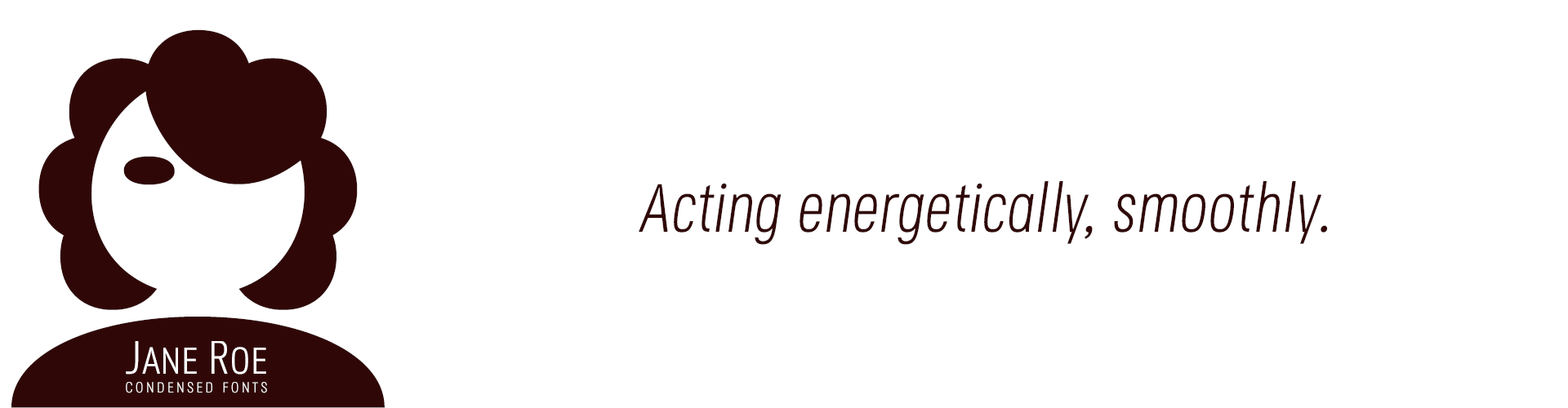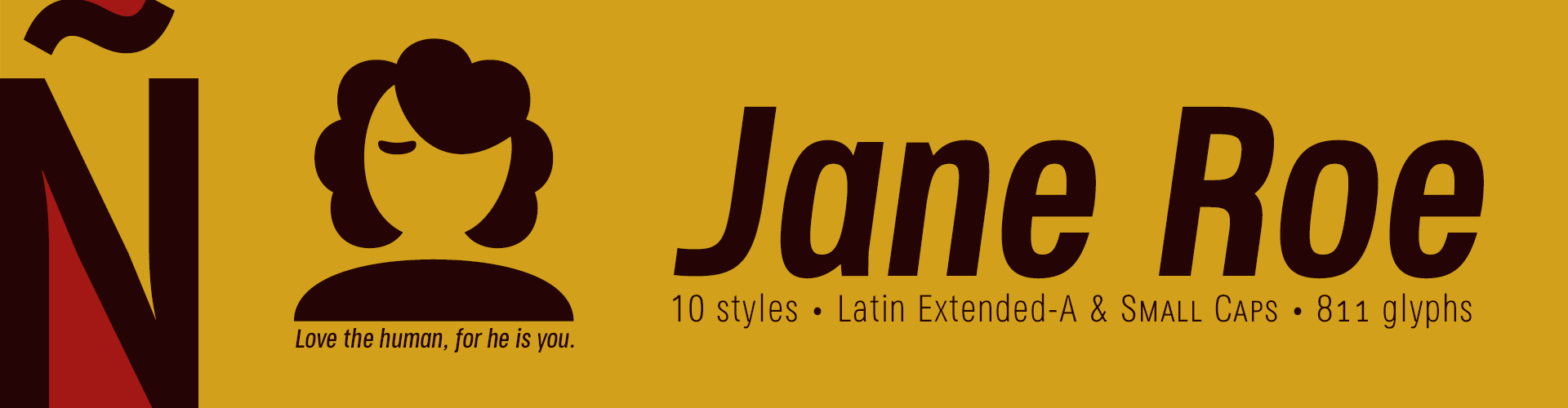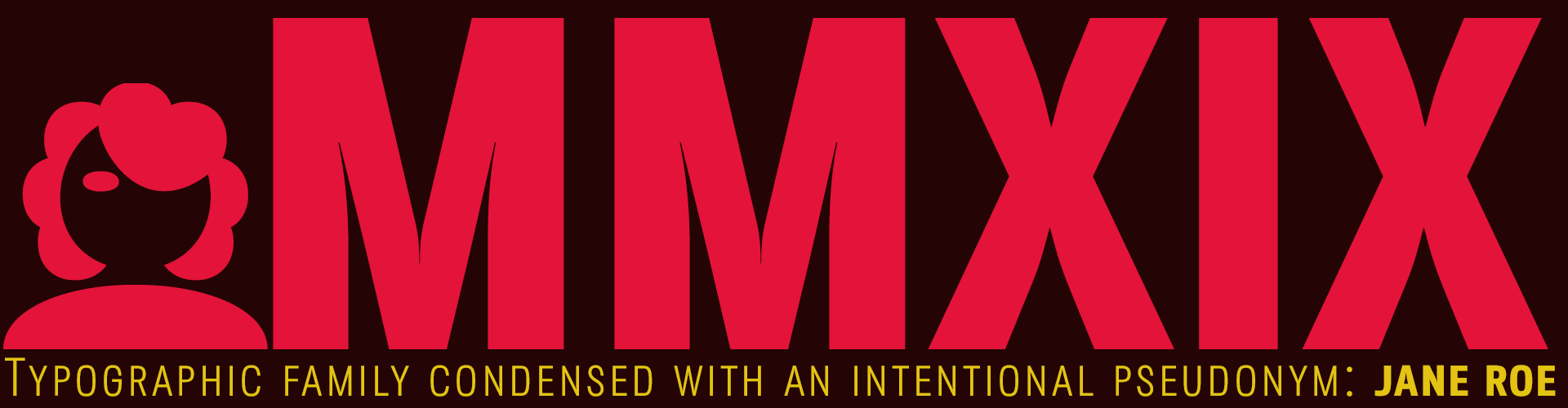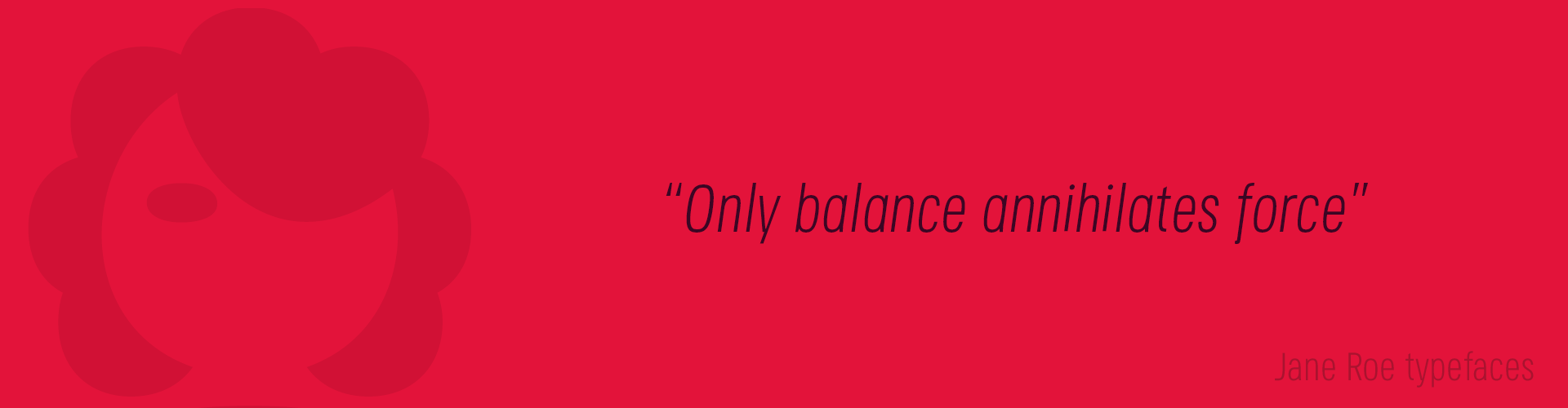
Acting energetically, smoothly!
Estilo: Sans Serif, Neo-Gothic, Condensed, Italic
Proporción: Light, Regular, Medium, Bold & Extra Bold
Funciones OpenType: Additional languages, All Alternates, Alternate Annotation Forms, Capital Spacing, Denominators, Discretionary Ligatures, Extended Fractions, Historical Forms, Historical Ligatures, Inferiors, Kerning, Localized Forms, Numerators, Oldstyle Figures, Optical Size, Ordinals, Scientific Inferiors, Slashed Zero, Small Capitals, Small Capitals From Capitals, Standard Ligatures, Subscript, Superior letters, Superiors, Superscript.
Esta tipografía contrapone su aspecto neutro con la modulación humanista de las astas en los caracteres dando la oportunidad de componer textos adaptables a cualquier contexto y concepto.